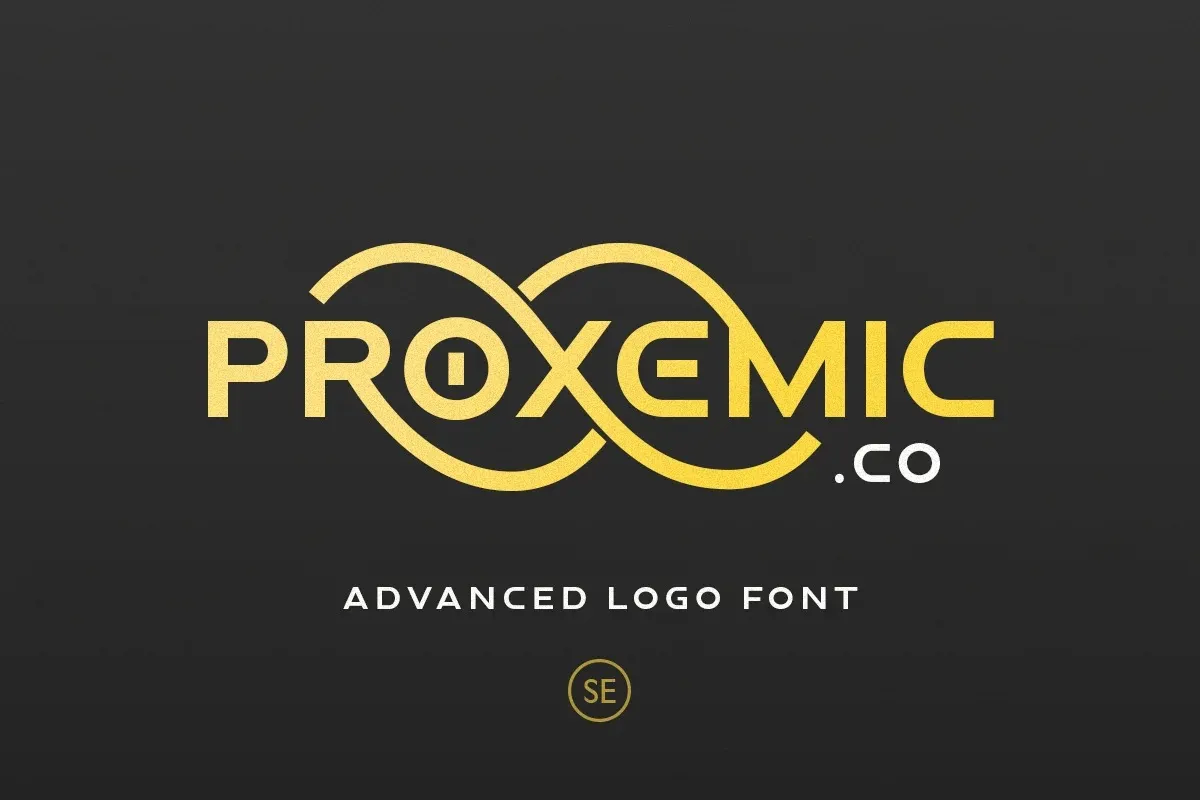
A Proxemic Font é uma elegante sans serif que combina formalidade com sofisticação, perfeitamente adequada para ambientes profissionais. Seu design limpo e minimalista se destaca na sua função de logomarca ou marca de empresa. Um dos elementos únicos desta fonte são suas minúsculas iniciais, que permitem criar um logotipo ainda mais impressionante com apenas alguns passos simples. Esta font é versátil o suficiente para ser utilizada em qualquer aplicação, especialmente para a criação de marcas visuais. Você pode misturar e combinar letras maiúsculas e minúsculas para dar ao seu logo uma aparência ainda mais sofisticada. Além disso, a Proxemic Font também oferece suporte à numeração, símbolos e línguas, tornando-a perfeitamente compatível com muitas necessidades de design. Engane-se em pensar que esta font é apenas para escrita ou uso digital; sua elegância e versatilidade a fazem uma escolha sólida para qualquer projeto gráfico.